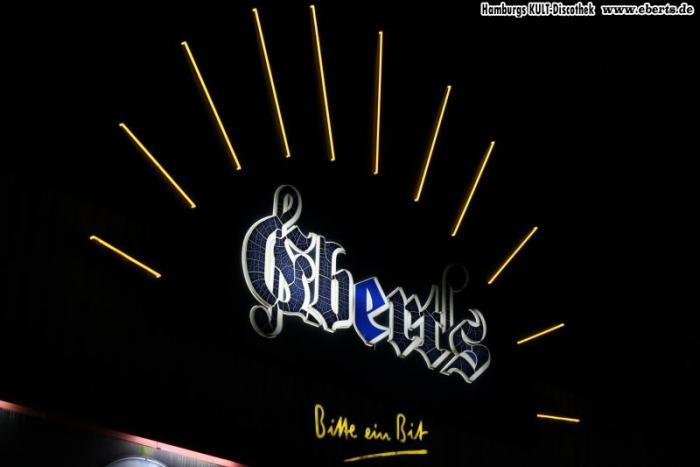
Suche nach einem Schriftsatz
Ich suche, für die Erstellung eines Logos eine Schrift.
Leider habe ich nur sehr, sehr wenige Zeichen, aber das "E" ist - so denke ich - sehr deutlich. Vielleicht kennt jemand die Schrift, aus der das Schild auf dem Foto erstellt wurde
www.eberts.de/partyfotos/782/category/2# ... dort das Bild 13Co43325 ganz unten auf der Seite in der Mitte